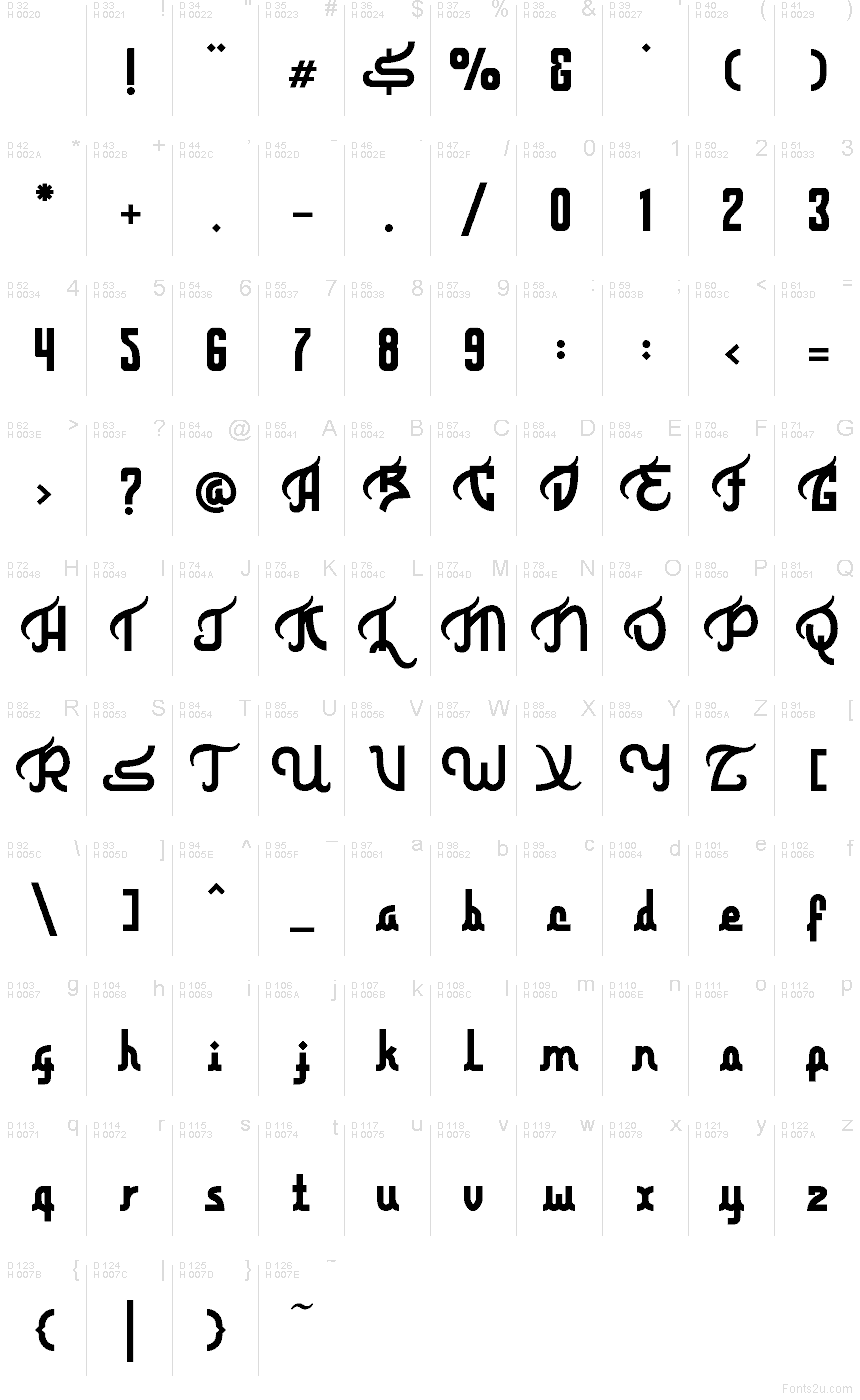
Hikma Glyphs od Putracetol Studio je bezplatné arabské písmo typu display, které zaujme svou kaligrafickou siluetou. Vysoké vzpřímené formy se zde snoubí s širokými křivkami a hákovitými zakončeními, která evokují arabskou literu. Kontrast mezi vertikálními tahy a plynulým pohybem doleva dodává designu ceremoniální rytmus, který ho odlišuje od běžných, neutrálních stylů.
Tento charakter dává smysl v grafikách k ramadánu, na plakátech k akcím, obalech halal produktů, knižních obálkách či v brandingu restaurací, kde musí být kulturní vliv patrný na první pohled. Krátké titulky a logotypy profitují především z vysokých oblouků a zakřivených koncovek, které vytvářejí silný kulturní podtón, aniž by přitom působily jako doslovná ručně psaná kaligrafie.